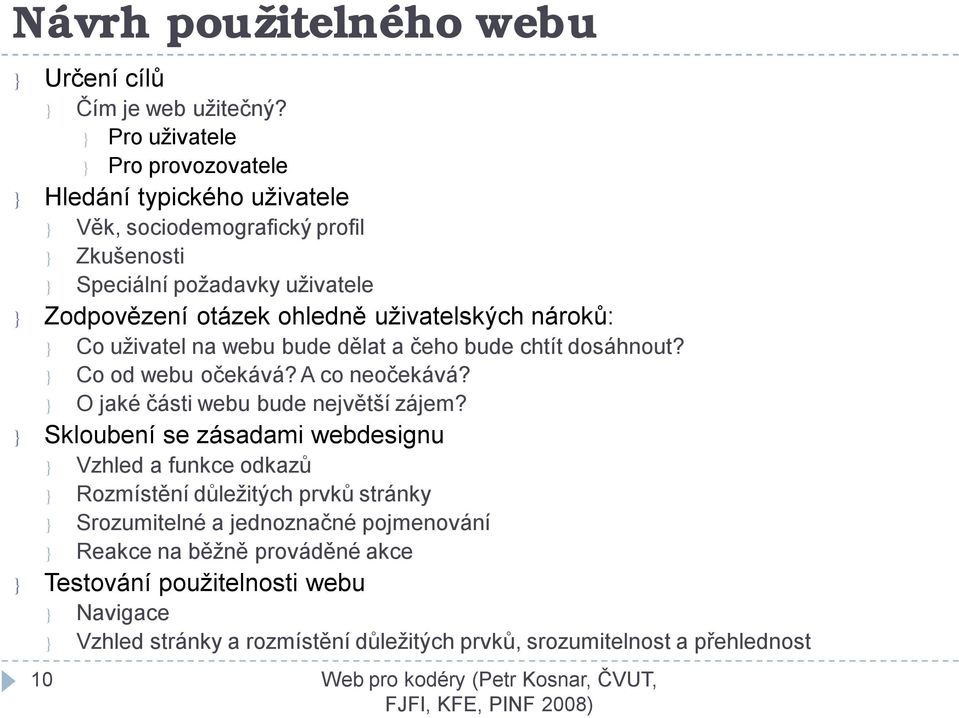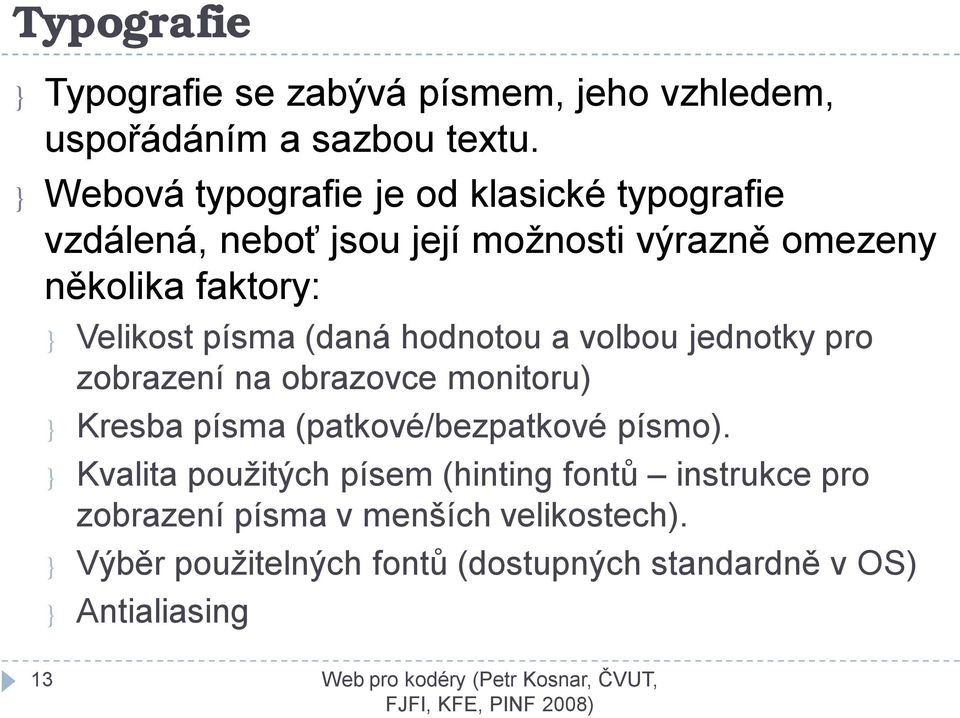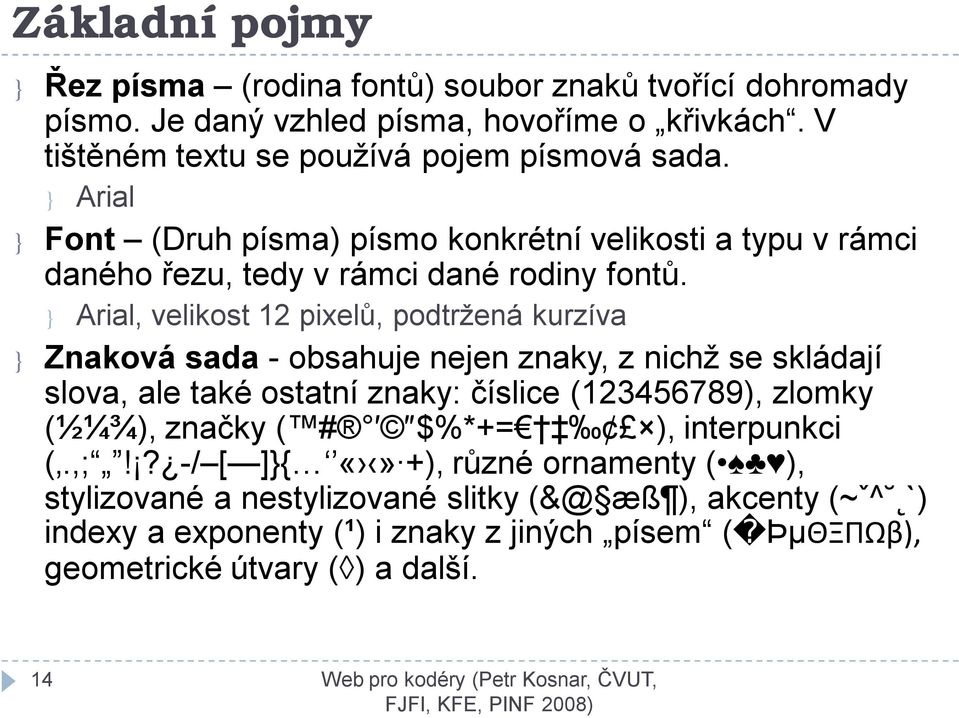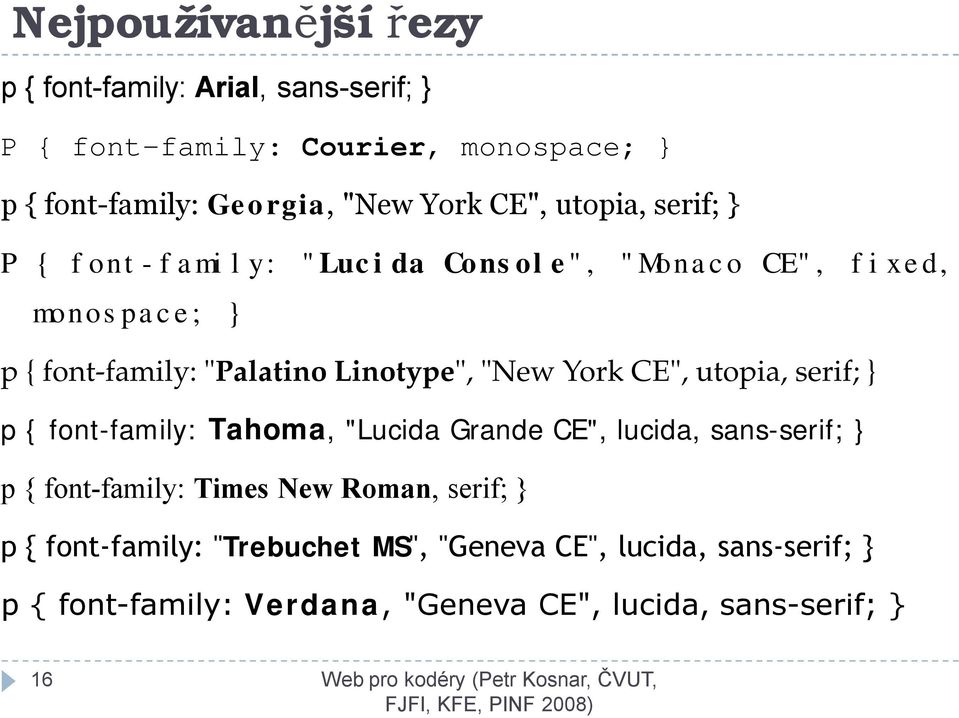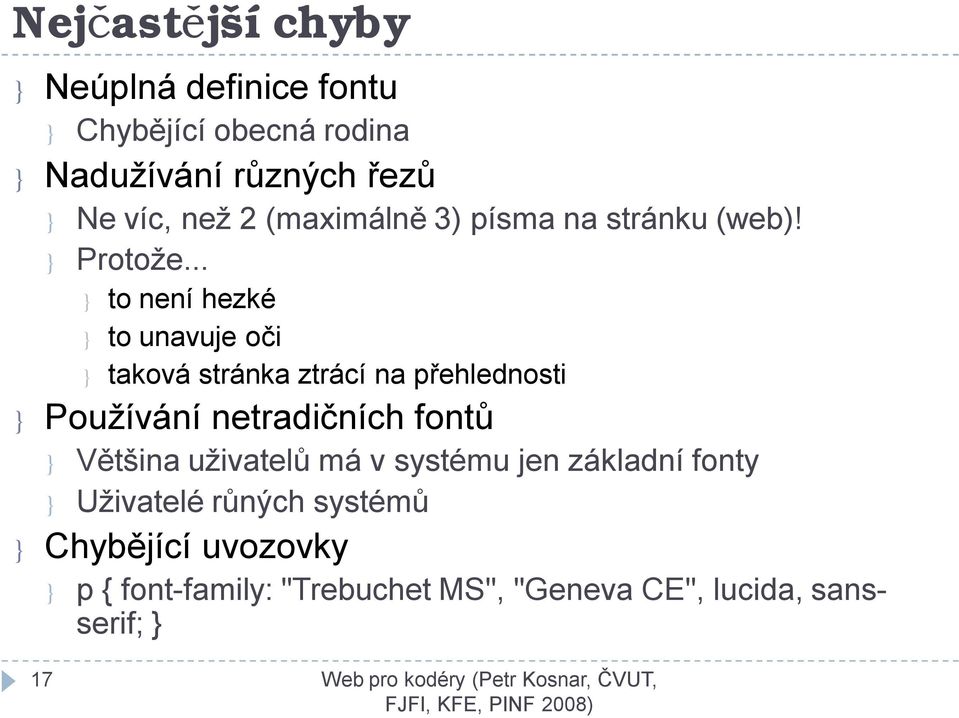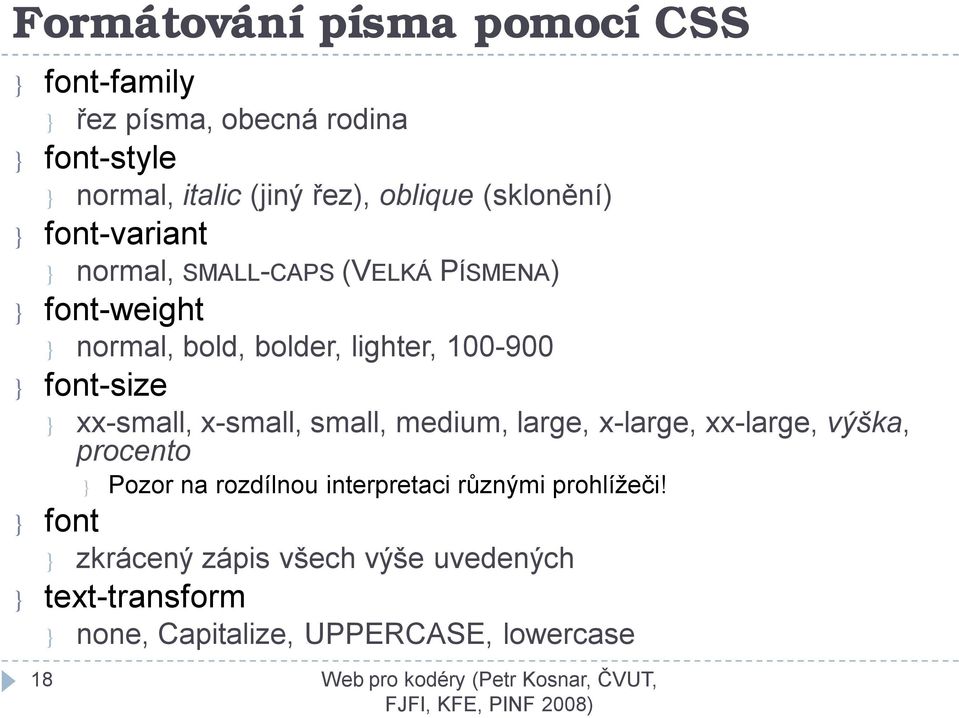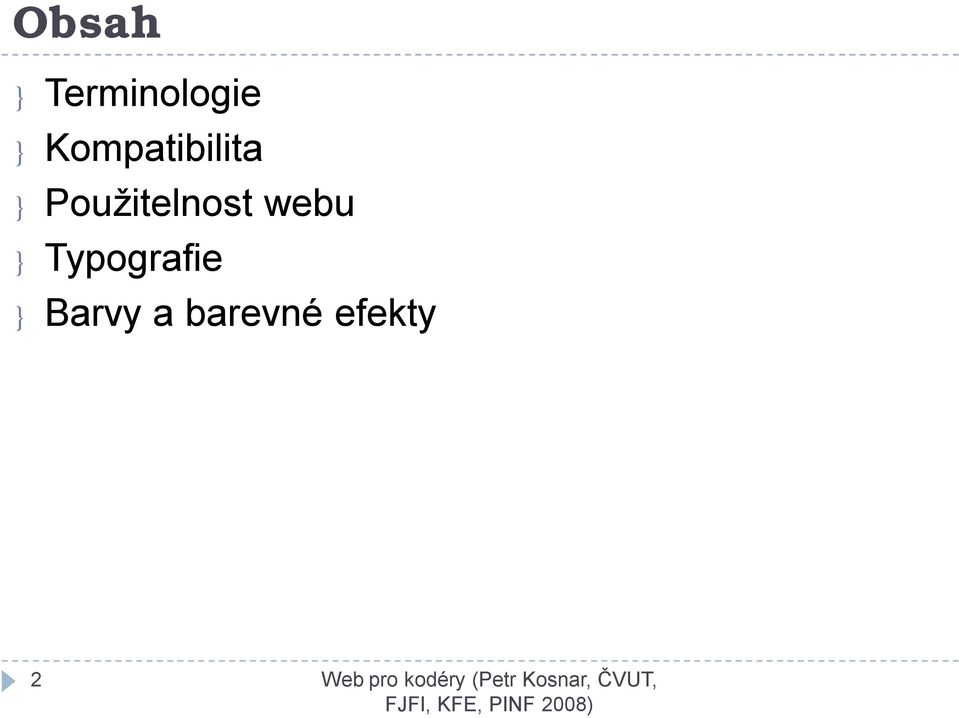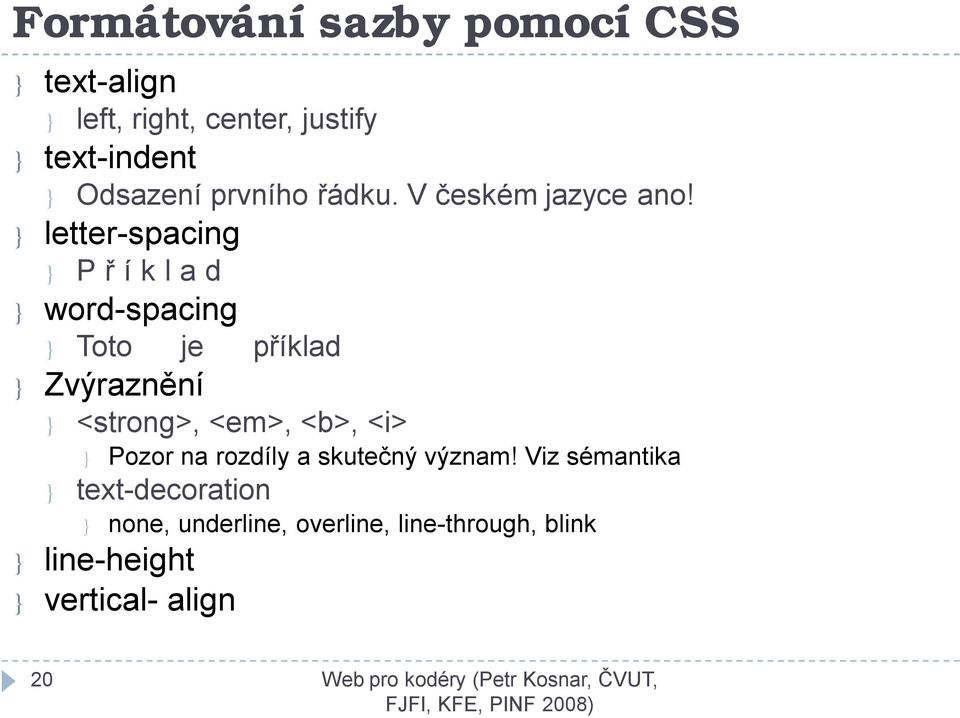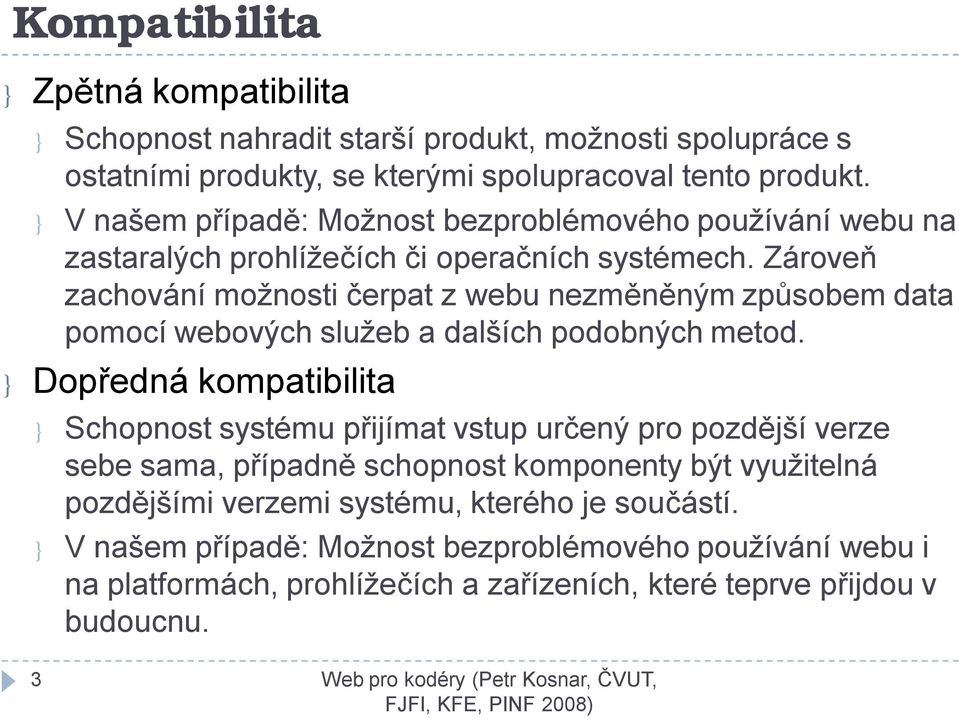
3. Kompatibilita, použitelnost a základy typografie. Web pro kodéry (Petr Kosnar, ČVUT, FJFI, KFE, PINF 2008)
1 3. Kompatibilita, použitelnost a základy typografie Web pro kodéry (Petr Kosnar, ČVUT,
2 Obsah } Terminologie } Kompatibilita } Použitelnost webu } Typografie } Barvy a barevné efekty 2
3 Kompatibilita } Zpětná kompatibilita } Schopnost nahradit starší produkt, možnosti spolupráce s ostatními produkty, se kterými spolupracoval tento produkt. } V našem případě: Možnost bezproblémového používání webu na zastaralých prohlížečích či operačních systémech. Zároveň zachování možnosti čerpat z webu nezměněným způsobem data pomocí webových služeb a dalších podobných metod. } Dopředná kompatibilita } Schopnost systému přijímat vstup určený pro pozdější verze sebe sama, případně schopnost komponenty být využitelná pozdějšími verzemi systému, kterého je součástí. } V našem případě: Možnost bezproblémového používání webu i na platformách, prohlížečích a zařízeních, které teprve přijdou v budoucnu. 3
4 Zpětná kompatibilita } Neexistuje stoprocentní zpětná kompatibilita } Přesněji: lze jí dosáhnout pouze vynaložením neúměrného úsilí a konečný výsledek je celkově vzato špatný. Navíc s minimální užitnou hodnotou. } Příklad: Netscape 1.0 nepodporuje ani HTML tabulky. Nemluvě o CSS, DOM a dalších vymoženostech posledních let. } Je potřeba si určit hranici zpětné kompatibility, kterou svým stránkám poskytneme (nejstarší podporovaný prohlížeč) } hlubší zpětná kompatibilita s sebou přináší rozšiřování kódu o nestandardní kusy kódu určené pro specifické zastaralé prohlížeče. Zároveň je potřeba nějaký obslužný mechanismus, který předloží zastaralým prohlížečům tu verzi stránek, která je jim určena. 4
5 Dopředná kompatibilita } Principielně obtížné, není znám budoucí vývoj. } Spoléhá se tedy na zpětně kompatibilní budoucí browsery } Dodržování standardů nejnovějších verzí XHTML přináší možnost větší interoperability a vysokou pravděpodobnost podpory do budoucna. } Nebude potřeba vytvářet vícero verzí stránky pro různé nové prohlížeče } Minimum problémů s dostupností díky všeobecné podpoře, oblíbenosti a rozvoji XML } Strukturální kód pro pozdější zpracovávání jako jakékoliv jiné XML 5
6 Platformy, prohlížeče, média } Počítejme s tím, že náš web by měl být přizpůsobený pro: } Operační systémy: } Windows, GNU/Linux, MacOS, PalmOS, Windows Mobile, Symbian } Prohlížeče: } Internet Explorer, Opera, Firefox, Safari, Opera mini } Zařízení: } PC, PDA, Smartphone, hlasová čtečka, projektor, tiskárna 6
7 Přirozená kompatibilita XHTML } XHTML jako člen rodiny XML je přirozeně kompatibilní s ostatními XML formáty a aplikacemi. } XHML zobrazují i zastaralé prohlížeče z dob, kdy specifikace XHTML neexistovala nebo byla v plenkách. } Jedna verze kódu pro všechny možnosit použití pro zobrazení na různých zařízeních, v různých prostředích a prohlížečích... } XHTML 1.0 existuje ve třech verzích: } Strict, Transitional a Frameset } Nejnovější verze: XHTML 1.1 } XHTML 2.0 ve stádiu Working Draft } XHTML má samozřejmě i své odpůrce 7
8 Použitelnost } Jak snadno uživatel najde na webu to, co hledá? } Jak snadno se uživatel naučí web ovládat? } Bude se muset na každé stránce se systémem znovu učit zacházet? } Když už se uživatel naučí web ovládat, jak efektivně s ním pracuje? } Jak dobře si zapamatuje styl ovládání webu? Přijde mu tento styl přirozený a nenásilný? } Kolik udělá uživatel při používání webu chyb? Dokáže nakonec splnit svůj cíl? Najde to, co hledal? } Je pro uživatele používání webu příjemné? Vrátí se? } Jsou informace, které uživatel našel platné a aktuální? 8
9 Myšlenka... Televizní stanice neříkají divákům, jak ovládat dálkový ovládač. Novináři neinstruují čtenáře, jak vyndat noviny ze schránky. Je čas, aby webové stránky přestaly říkat návštěvníkům, jak ovládat odkazy. Jason Roberts 9
10 Návrh použitelného webu } Určení cílů } Čím je web užitečný? } Pro uživatele } Pro provozovatele } Hledání typického uživatele } Věk, sociodemografický profil } Zkušenosti } Speciální požadavky uživatele } Zodpovězení otázek ohledně uživatelských nároků: } Co uživatel na webu bude dělat a čeho bude chtít dosáhnout? } Co od webu očekává? A co neočekává? } O jaké části webu bude největší zájem? } Skloubení se zásadami webdesignu } Vzhled a funkce odkazů } Rozmístění důležitých prvků stránky } Srozumitelné a jednoznačné pojmenování } Reakce na běžně prováděné akce } Testování použitelnosti webu } Navigace } Vzhled stránky a rozmístění důležitých prvků, srozumitelnost a přehlednost 10
11 Nezapomeňte... } Přehledná a intuitivní navigace, odkazy naznačují co se pod nimi skrývá } Navigační menu, nadpis webu, případně logo umístit na všech stránkách na stejném místě } Na každé stránce by mělo být uživateli zřejmé, kde se v rámci webu nachází a jaký je účel této stránky } Z každé stránky by měl vést odkaz na úvodní stránku a na hlavní stránku sekce, ve které se nachází } Pořadí, velikost a výraznost prvků odpovídají jejich významu a důležitosti } Není na stránce něco zbytečně, nějaký rušivý element? 11
12 12
13 Typografie } Typografie se zabývá písmem, jeho vzhledem, uspořádáním a sazbou textu. } Webová typografie je od klasické typografie vzdálená, neboť jsou její možnosti výrazně omezeny několika faktory: } Velikost písma (daná hodnotou a volbou jednotky pro zobrazení na obrazovce monitoru) } Kresba písma (patkové/bezpatkové písmo). } Kvalita použitých písem (hinting fontů instrukce pro zobrazení písma v menších velikostech). } Výběr použitelných fontů (dostupných standardně v OS) } Antialiasing 13
14 Základní pojmy } Řez písma (rodina fontů) soubor znaků tvořící dohromady písmo. Je daný vzhled písma, hovoříme o křivkách. V tištěném textu se používá pojem písmová sada. } Arial } Font (Druh písma) písmo konkrétní velikosti a typu v rámci daného řezu, tedy v rámci dané rodiny fontů. } Arial, velikost 12 pixelů, podtržená kurzíva } Znaková sada - obsahuje nejen znaky, z nichž se skládají slova, ale také ostatní znaky: číslice ( ), zlomky (½¼¾), značky ( # $%*+= ), interpunkci (.,;!? -/ [ ]}{ +), různé ornamenty ( ), stylizované a nestylizované slitky (&@ æß ), akcenty (~ˇ^ `) indexy a exponenty (¹) i znaky z jiných písem ( ÞµΘΞΠΩβ), geometrické útvary ( ) a další. 14
15 Obecné rodiny písem Obecná rodina Popis Typická písma Ukázka sans-serif Bezpatkové písmo Arial, Helvetica sans-serif serif monospace Patkové písmo Neproporcionální písmo Times New Roman, Times Courier, Courier New serif monospace fantasy Ozdobné písmo různé FANTASY cursive Ozdobná kursiva různé cursive Patkové a bezpatkové písmo dostalo svůj název podle zobáčků, tedy patek (či jejich absence) na otevřených koncích křivek, které tvoří danou literu. Neproporcionální znamená, že všechny znaky takového řezu mají stejnou horizontální šířku (využívá se k prezentaci zdrojových kódů, atp.) 15
16 Nejpoužívanější řezy p { font-family: Arial, sans-serif; } P { font-family: Courier, monospace; } p { font-family: Georgia, "New York CE", utopia, serif; } P { font-family: "Lucida Console", "Monaco CE", fixed, monospace; } p { font-family: "PalatinoLinotype", "New York CE", utopia, serif; } p { font-family: Tahoma, "Lucida Grande CE", lucida, sans-serif; } p { font-family: Times New Roman, serif; } p { font-family: "Trebuchet MS", "Geneva CE", lucida, sans-serif; } p { font-family: Verdana, "Geneva CE", lucida, sans-serif; } 16
17 Nejčastější chyby } Neúplná definice fontu } Chybějící obecná rodina } Nadužívání různých řezů } Ne víc, než 2 (maximálně 3) písma na stránku (web)! } Protože... } to není hezké } to unavuje oči } taková stránka ztrácí na přehlednosti } Používání netradičních fontů } Většina uživatelů má v systému jen základní fonty } Uživatelé růných systémů } Chybějící uvozovky } p { font-family: "Trebuchet MS", "Geneva CE", lucida, sansserif; } 17
18 Formátování písma pomocí CSS } font-family } řez písma, obecná rodina } font-style } normal, italic (jiný řez), oblique (sklonění) } font-variant } normal, SMALL-CAPS (VELKÁ PÍSMENA) } font-weight } normal, bold, bolder, lighter, } font-size } xx-small, small, medium, large, x-large, xx-large, výška, procento } Pozor na rozdílnou interpretaci různými prohlížeči! } font } zkrácený zápis všech výše uvedených } text-transform } none, Capitalize, UPPERCASE, lowercase 18
19 Sazba textu } Neznámá šířka řádku } -> nelze zabránit vzniku tzv. Řek } Řeky - nepřiměřeně velké mezislovní mezery, které na sebe vhorším případě ještě ve vertikálním směru navazují } Neznámá velikost písma } Uživatelské nastavení v prohlížeči } Šířka řádku nejlépe znaků (včetně mezer) } Nepoužívat sazbu do bloku 19
20 Formátování sazby pomocí CSS } text-align } left, right, center, justify } text-indent } Odsazení prvního řádku. V českém jazyce ano! } letter-spacing } P ř íklad } word-spacing } Toto je příklad } Zvýraznění } <strong>, <em>, <b>, <i> } Pozor na rozdíly a skutečný význam! Viz sémantika } text-decoration } none, underline, overline, line-through, blink } line-height } vertical- align 20
21 Entity } Entity se používají k zapisování nestandardních znaků, pokud nám jejich zapsání neumožňuje použité kódování } Kódování UTF-8 znaky zapisované entitami obsahuje! } Entita se zapisuje ve tvaru &jmeno_entity; 21
22 Mezery } Nedělitelná (zúžená mezera se nepoužívá kvůli slabé podpoře prohlížečů) } Mezi iniciálou a příjmením (P. Kosnar) } Mezi titulem a příjmením (Ing. Novák) } Ve víceslovném názvu (Windows XP) } Mezi hodnotou a jednotkou (10 cm) } Jako oddělovač řádů ( ) } Mezi hodnotou a znakem procenta (účinnost je asi 23 %) } Datumy ( ) } Mezi paragraf a jeho číslo ( 111) } Okolo symbolu & (Plug & Play) } U poměrů (1 : 10) } V matematických vzorcích ( = 30) } Zajišťuje, že se jednopísmenná předložka, spojka či libovolný jeden znak nikdy neobjeví na konci řádku. } Výjimka -spojky a a i vsouřadném poměru, nikoliv však na začátku věty. 22
23 Mezeru nepíšeme } u sportovních výsledků: } Sparta-Slavia: 0:0 } je-li jednotka ve funkci přídavného jména: } 60W žárovka, 10 pivo } před symbol procenta ve smyslu přídavného jména: } 3% úrok (tříprocentní úrok) } při uvádění velikosti úhlu nebo obsahu alkoholu (přestože se jedná o jednotky): } 360, 10 } okolo lomítek: } km/h } za desetinnou čárkou: } 23,4 } u násobků: } 10krát, 10násobně, 10 (10 ) } u časů ve sportovních výsledcích: } viz později Pozor, změna možná významu! zápis x=1-3 můžeme reprodukovat jako: rozsah proměnné x = 1 3 rovnici x =
24 Pomlčka -+ } Spojovník } Spojování slov, } Praha2-Vinohrady, Frýdek-Místek, literárně-hudební soubor, česko-německý slovník } k připojení zvratné částice "li } bude-li, chcete-li } Mínus } Operační symbol s mezerami } 10 3 = 7 } Záporná čísla bez mezer } Teplota dosáhla 18,5 C. } En-pomlčka } ve funkci spojky či předložky (bez mezer) } utkání Sparta Slavia(ve významu proti), } dvojice Voskovec Werich (a), } linka Praha Brno (z-do), } vláda KSČ v letech (od-do). } přestávka v řeči nebo vypuštěného slova (s mezerou) } Můj dům můj hrad. } Volnost rovnost bratrství. } označení celých peněžních částek } Časopis je za Kč 69, 24
25 Způsoby psaní speciálních údajů } Telefonní (faxová) čísla } Mezinárodní formát nnn nnn nnn } } Poštovní směrovací čísla } nnn nn } } Kalendářní data } Den, měsíc a rok oddělujeme pomocí } 24. ledna 2010, } Hodiny a minuty oddělujeme tečkou, minuty a sekundy dvojtečkou, sekundy a setiny sekund desetinnou čárkou, (mezery se nepíšou). } hod, 2 h 30 min, 3:15,23 min. } J. N. uběhl trať v čase 5:32:15,25 (tzn. 5 hodin, 32 minut, 15 sekund a 25 setin sekundy). } Rok můžeme zkrátit na dvě číslice v případě spojení dvou letopočtů spojovníkem či lomítkem ( , 1994/95) nebo ve zvláštních spojeních (INVEX 99, INVEX 99). Nebo v případě výtvarného zájmu. 25
26 Další často používané entity } Matematické znaky. } ± ± } } } } } } ¼ ¼ } ½ ½ } ¾ ¾ } Uvozovky } Horní } dolní } Další... } } } } } 26
27 Interpunkce } Mezera } za interpunkčním znaménkem, nikoliv před. } Říkal, že firma ABC, s. r. o., která zde sídlila, je zrušená. } Výpustka (trojtečka) } tam, kde je vypuštěná či nedopovězená část věty } Ještě jednou mi zasedneš místo a } Pomlčka ani spojovník nesmí stát na začátku řádku } Mladí ležáci staří žebráci. } Apostrof nahrazuje vynechané písmeno. ' } Na požádání si stáh' i kalhoty. 27
28 Skladba stránky } Úvodní odstavec krátký (11 slov) } Titulek, podtitulek, perex, mezititulky } Číslované výčty místo nečíslovaných (odrážkových) } volný řádek mezi odstavci (vertikální odsazení) } Čím méně zvýraznění, tím čitelnější text } Má-li být text zviditelněn, dejme mu víc volného prostoru } Dlouhé řádky se obtížně čtou } Rozdělení: Záhlaví, hlavní obsah, pata 28
29 Barvy a grafické efekty } Musí být zajištěn dostatečný kontrast } Aby byla stránka čitelná i na nekvalitním nebo poškozeném monitoru, displeji osvětleném sluncem... } Minimum rušivých grafických efektů } Blikání, výrazné barevné kombinace, mnoho barev pohromadě 29
30 Kontrast Je nutný dostatečný rozdíl v odstínu, nasycení a světlosti 30
31 Další informace } } } } Steve Krug: Don t Make Me Think } Jakob Nielsen: Usability Engineering } Jesse J. Garrett: The Elements of User Experience } Pavel Kočička, Filip Blažek: Praktická typografie, Computer Press, Brno, 2004, ISBN } } } } } } } } } 31
32 Kontrolní úkol } Vytvořte stránku s nějakým odborným obsahem, kde jsou smysluplně využité alespoň 4 různé XHTML entity. } Stránku graficky zpracujte, aby působila jednoduše, přehledně a její obsah byl čitelný. } Ocením originální estetické zpracování } Avšak pozor na respektování pravidel z této přednášky! } Požadavky: } Validní a sémanticky správný XHTML a CSS } Oddělení obsahu od prezentace } Dodržení zásad kompatibility a snadné použitelnosti } Dodržení typografických pravidel } Odpovídající barevné zpracování 32
Základní typografická pravidla
Základní typografická pravidla 1. část materiál pro 12IPG J. Blažej, 2012 Úvod Typografie se zabývá písmem, jeho vzhledem, uspořádáním a sazbou textu. umělecko-technický obor ne vždy jasná pravidla legislativa
KASKÁDOVÉ STYLY - PÍSMO
KASKÁDOVÉ STYLY - PÍSMO Název školy Obchodní akademie, Vyšší odborná škola a Jazyková škola s právem státní jazykové zkoušky Uherské Hradiště Název DUMu Kaskádové styly písmo Autor Zdeněk Hrdina Datum
Maturitní otázka číslo 23 strana 1 z 5. Typografie
Maturitní otázka číslo 23 strana 1 z 5 Typografie je vědní obor zabývající se sázením textu, hlavně jeho grafickou stránkou. S příchodem počítačů máme k dispozici různé DTP programy (DeskTop
Střední průmyslová škola a Vyšší odborná škola technická Brno, Sokolská 1
Střední průmyslová škola a Vyšší odborná škola technická Brno, Sokolská 1 Šablona: Název: Téma: Autor: Inovace a zkvalitnění výuky prostřednictvím ICT Design a vzhledové vlastnosti webových stránek Vlastnosti
Počítačová typografie
Počítačová typografie Typografie je nauka o tom, jak má tiskovina vypadat. Proč se o typografii učíme? Každý z nás běžně připravuje nějakou tiskovinu a požadavky na její kvalitu a zpracování jsou všude
Předmět: Typografie na webu
Registrační číslo projektu: CZ.1.07/1.4.00/21.3712 Škola adresa: Základní škola T. G. Masaryka Ivančice, Na Brněnce 1, okres Brno-venkov, příspěvková organizace Na Brněnce 1, Ivančice, okres Brno-venkov
Návrh stránek 4IZ228 tvorba webových stránek a aplikací
4IZ228 tvorba webových stránek a aplikací Jirka Kosek Poslední modifikace: $Date: 2013/12/12 20:40:58 $ Obsah Úvod... 3 Recept na dobré webové stránky... 4 Použitelnost... 5 Jak se pozná použitelný web...
Blokový model v CSS:
Blokový model v CSS: Vlastnosti textu Vlastnost Hodnoty Standardní hodnota Aplikuje se na Dědí se Popis word-spacing normal, délka normal o kolik se zvětší mezera mezi slovy letter-spacing
Webová grafika, struktura webu a navigace, použitelnost a přístupnost
Webová grafika, struktura webu a navigace, použitelnost a přístupnost Martin Kuna martin.kuna@seznam.cz Obsah Webová grafika Rozvržení stránky Typografické zásady Nejčastější chyby Struktura webu a navigace
T Y P O G R A F I E. Tvorba textových dokumentů
T Y P O G R A F I E Tvorba textových dokumentů Počítačová typografie nauka o tom, jak má tiskovina vypadat typus = znak, grafó = píši současné programové vybavení a možnost kvalitního tisku každý může
Word textový editor. Tlačítko Office základní příkazy pro práci se souborem. Karta Domů schránka. písmo. vyjmout. vložit kopírovat.
Word textový editor Tlačítko Office základní příkazy pro práci se souborem Karta Domů schránka vyjmout vložit kopírovat formát písmo velikost písma volba písma barva písma tučné podtržené zvýraznění
pravidla pro grafickou úpravu textů při práci s textovými editory:
Zásady pro vypracování seminární a maturitní práce Úprava písemností zpracovaných textovými editory norma ČSN 01 6910 pravidla pro grafickou úpravu textů při práci s textovými editory: určuje způsob psaní
Přehled základních html tagů
Přehled základních html tagů h1... hlavní nadpis h2... podnadpisy h3... podnadpisy další úrovně p... odstavec strong... tučné písmo b... tučné písmo em... kurzíva i... kurzíva br... zalomení řádku ol...
TVORBA WEBOVÝCH STRÁNEK
TVORBA WEBOVÝCH STRÁNEK Výukový modul TWS_03b Ing. Pavel Chmiel, Ph.D. UNIV 2 - KRAJE Osnova výukového modulu TWS_03b 1. Kaskádové styly (CSS) 2. Vazba CSS na (X)HTML dokument 3. Syntaxe CSS 4. Barva a
Letem ke klíčovým kompetencím aneb Pohádkou o Raškovi to nekončí Metodický materiál ZŠ a MŠ Frenštát pod Radhoštěm, Tyršova 913 2009 2011
Letem ke klíčovým kompetencím aneb Pohádkou o Raškovi to nekončí Metodický materiál ZŠ a MŠ Frenštát pod Radhoštěm, Tyršova 913 2009 2011 Zpracování: Mgr. Marek Křištof ZŠ a MŠ Frenštát pod Radhoštěm,
Fonty - praxe, obecné rodiny
Fonty - praxe, obecné rodiny Windows, fonty, internet? Většina profesionálních webových tvůrců operuje nejvýše s těmito základními řezy: Arial, Courier New, Georgia, Lucida Console, Palatino Linotype,
ZÁKLADY PRÁCE S PC MS Word. Mgr. Petr Jakubec
ZÁKLADY PRÁCE S PC MS Word Mgr. Petr Jakubec 1 Nejdůležitější panely: Vložit Konce stránek, Konce oddílů, Čísla stránek, Symboly, Odkazy (Poznámka pod čarou, Titulek,...) Formát Písmo, Odstavce, Odrážky
Základní typografická pravidla
Základní typografická pravidla materiál pro 12IPG J. Blažej, 2017 Úvod Typografie se zabývá písmem, jeho vzhledem, uspořádáním a sazbou textu. umělecko-technický obor ne vždy jasná jednoznačná pravidla
Referenční přehled vlastností CSS1 (Cascading Style Sheets, level 1)
Stránka č. 1 z 9 Referenční přehled CSS1 (Cascading Style Sheets, level 1) Tento dokument shrnuje jdůležitější informace o káskadových stylech dokumentů. Informace vycházejí z oficialního doporučení konsorcia
FORMÁLNÍ NÁLEŽITOSTI PRÁCE TOMÁŠ LÁZNA ZÁŘÍ 2015 T.LAZNA@GMAIL.COM
FORMÁLNÍ NÁLEŽITOSTI PRÁCE TOMÁŠ LÁZNA ZÁŘÍ 2015 T.LAZNA@GMAIL.COM PRÁCE SOČ 20 30 stran + přílohy Obvyklá struktura Pravopis Grafická úprava, typografie Vazba typicky kroužková nebo hřbet STRUKTURA ODBORNÉ
! Nauka o tom, jak má tiskovina vypadat. ! dobře čitelná. ! snadná orientace v textu. ! estetické působení. ! Klasické umělecké řemeslo
Počítačová typografie úvod Aplikační software na PC Počítačová typografie původní verze Mgr. Lucie Pelikánová úpravy a rozšíření RNDr. Jan Preclík! Nauka o tom, jak má tiskovina vypadat! dobře čitelná!
Typografická a estetická pravidla. Daniela Špačková
Typografická a estetická pravidla Daniela Špačková Používání a kombinování písem Pro tištěné texty: písmo patkové, např. Times New Roman Pro prezentace: písmo bezpatkové, např. Arial Nadpisy mohou být
Textové editory. Ing. Luděk Richter
Textové editory Ing. Luděk Richter Střední škola, Havířov-Šumbark, Sýkorova 1/613, příspěvková organizace Tento výukový materiál byl zpracován v rámci akce EU peníze středním školám - OP VK 1.5. Výuková
Kaskádové styly (CSS) Cascading Style Sheets
CSS verze 22.11. 2007 1 Kaskádové styly (CSS) Cascading Style Sheets Existují 3 druhy zápisu CSS do webové stránky a) Vložením tagu STYLE do hlavičky dokumentu ...definice stylu atributy: type...
STANDARDNÍ APLIKAČNÍ VYBAVENÍ
Projekt Pospolu Práce s textovým procesorem STANDARDNÍ APLIKAČNÍ VYBAVENÍ Autorem materiálu a všech jeho částí, není-li uvedeno jinak, je Bohuslava Čežíková. Struktura prezentace textový dokument písmo
Referenční přehled vlastností CSS1 (Cascading Style Sheets, level 1)
Referenční přehled CSS1 (Cascading Style Sheets, level 1) Tento dokument shrnuje jdůležitější informace o káskadových stylech dokumentů. Informace vycházejí z oficialního doporučení konsorcia W3C Cascading
Střední škola průmyslová a umělecká, Opava, příspěvková organizace, Praskova 399/8, Opava, 746 01 IČO: 47813121 Projekt: OP VK 1.5
Název a adresa školy: Střední škola průmyslová a umělecká, Opava, příspěvková organizace, Praskova 399/8, Opava, 746 01 IČO: 47813121 Projekt: OP VK 1.5 Název operačního programu: OP Vzdělávání pro konkurenceschopnost
Pomocník aneb Když hlava nepostačí
Pomocník aneb Když hlava nepostačí Obsah I. Interpunkční znaménka... 2 Tečka... 2 Čárka... 2 Dvojtečka... 3 Středník... 3 Uvozovky... 3 Apostrof... 3 Spojovník/pomlčka/dlouhá pomlčka... 3 Tři tečky...
Typografická pravidla
VY_32_INOVACE_In 6.,7.05 Typografická pravidla Anotace: Žák se seznámí s typografickými pravidly. Procvičí využití typografických pravidel v praxi. Pracuje na svém žákovském počítači. Vzdělávací oblast:
Typografické míry. Měrné systémy: 1. evropský, tzv. Didôtův. 2. anglosaský. Základní jednotka je typografický bod.
Typografické míry Měrné systémy: 1. evropský, tzv. Didôtův 2. anglosaský Základní jednotka je typografický bod. E 1 b = 0.3759 mm cicero 12 b A 1 pt= 0.351 mm pica 12 pt 02 1 Měrné jednotky TEXu: pt pc
KAPITOLA 3 - ZPRACOVÁNÍ TEXTU
KAPITOLA 3 - ZPRACOVÁNÍ TEXTU KLÍČOVÉ POJMY textové editory formát textu tabulka grafické objekty odrážky a číslování odstavec CÍLE KAPITOLY Pracovat s textovými dokumenty a ukládat je v souborech různého
Typografická pravidla - úvod
Typografická pravidla - úvod Základní doporučení: Nejdříve napište celý dokument základním písmem, potom teprve formátujte (písmo, odstavec, stránku). Klávesa ENTER se používá POUZE NA KONCI ODSTAVCE,
Publikační manuál GJO Litovel
Publikační manuál GJO Litovel Jak by měly naše dokumenty vypadat? Nastavení stránky Okraje z každé strany 2,5 cm U vícestránkových dokumentů číslovat strany. Formát číslování 1, zarovnat na střed zápatí.
Normalizovaná úprava písemností ČSN
Normalizovaná úprava písemností ČSN 01 6910 www.zlinskedumy.cz 3. Textový sloupec Zahrnuje: Papíry a formáty papíru Druhy a velikost písma Mezery - probrané v samostatné kapitole spolu s pevnými spojeními
CSS (Cascading Style Sheets) Jak se zapisují? externí soubory s koncovkou.css. přímo do www stránky
CSS (Cascading Style Sheets) Jak se zapisují? externí soubory s koncovkou.css přímo do www stránky Externí soubory: stránka se styly
Gymnázium a Střední odborná škola, Rokycany, Mládežníků 1115
Číslo projektu: Gymnázium a Střední odborná škola, Rokycany, Mládežníků 1115 Číslo šablony: 5 Název materiálu: Ročník: Identifikace materiálu: Jméno autora: Předmět: Tématický celek: Anotace: CZ.1.07/1.5.00/34.0410
- Byl změněn způsob psaní dat a časových údajů (podle ČSN EN 28601);
ČESKÁ NORMA ICS 01.140.30 1997 Úprava písemností psaných strojem nebo zpracovaných textovými editory ČSN 01 6910 Srpen Guidelines for Typewriting and Text Presentation Règles pour la dactylographie et
Řekl: V létě 89 zemřela. d Artagnan
x Apostrof odsuvník neplést s jednoduchou uvozovkou Používá se pro vynechání části letopočtu: jaro 98. V cizích jazycích: d Artagnan. porovnejte tvar Řekl: V létě 89 zemřela. d Artagnan x Uvozovky Přisazují
Odkazy se v normálním případě podtrhávají samy, není nutno to nastavovat.
Úprava textu Všechny tagy na formátování textu jsou in-line tagy, to znamená řádkové. Nezalamují za sebou řádek (narozdíl od blokových tagů). Fyzické formátování říká, jak má který
Pravidla pro estetickou úpravu textu
Pravidla pro estetickou úpravu textu Pro vytváření dobře vypadajících dokumentů existují osvědčené zásady a pravidla pro to, aby naše dokumenty byly nejen technicky, ale i esteticky na výši. Používání
Typografie. pro každý den
Typografie pro každý den Okouzlete zákazníka svým designem! Typografie pro každý den! Leták? To zvládnu sám! Znáte to? Asi ano. Každý z nás už musel něco vytvořit. Ať to byl úřední dopis, leták nebo třeba
CSS - stručná reference kaskádových stylů
1. font a parametry písma font, font-family, font-size, font-style, font-variant, font-weight 1.1 font Nastavuje většinu parametrů textu najednou. Jednotlivé atributy naleznete v kapitolách 1.2-1.6 a line-height
PSANÍ ODBORNÉHO TEXTU (např. SOČ, seminární práce)
PSANÍ ODBORNÉHO TEXTU (např. SOČ, seminární práce) Každý text nás reprezentuje, u odborných textů to platí obzvlášť Vše je posuzováno ze tří hledisek (nic z toho se nesmí zanedbat): obsah podloženost tvrzení,
Pokyny k vypracování absolventské práce
Základní škola a Mateřská škola Bělá pod Pradědem, příspěvková organizace tel.: 584 412 084 e-mail: zsadolfovice@jen.cz Adolfovice 170 web: http://zsadolfovice.cz IČO: 75029456 790 01 Jeseník Pokyny k
Reprodukce textových předloh
fialar@kma.zcu.cz Podpořeno z projektu FRVŠ 584/2011 Druhy sazby Podle technologie typografická sazba fotosazba počítačová sazba (DTP, DeskTop Publishing) Podle obsahu a účelu hladká (sazba převážně jedním
Publikační manuál GJO Litovel
Publikační manuál GJO Litovel Jak by měly naše dokumenty vypadat? Nastavení stránky Okraje z každé strany 2,5 cm. (Menu Soubor/Vzhled stránky) U vícestránkových dokumentů číslovat strany. Formát číslování
Základní typografická pravidla
Variace 1 Základní typografická pravidla Autor: Mgr. Jaromír JUŘEK Kopírování a jakékoliv další využití výukového materiálu je povoleno pouze s uvedením odkazu na www.jarjurek.cz. 1. Základní typografická
Střední průmyslová škola strojnická Vsetín. Předmět Druh učebního materiálu Typografická pravidla pro psaní dokumentů
Název školy Číslo projektu Autor Střední průmyslová škola strojnická Vsetín CZ.1.07/1.5.00/34.0483 Ing. Martin Baričák Název šablony III/2 Název DUMu 1.2 Základní typografická pravidla I. Tematická oblast
Mimochodem, co je CSS? Formátování HTML. Drobný problém. Základy práce se styly. Trojí použití CSS. Přímo (in-line)
Mimochodem, co je CSS? CSS vzniklo někdy kolem roku 1997. Je to kolekce metod pro grafickou úpravu webových stránek. Ta zkratka znamená Cascading Style Sheets, česky "kaskádové styly". Kaskádové, protože
PODPORA ELEKTRONICKÝCH FOREM VÝUKY
I N V E S T I C E D O R O Z V O J E V Z D Ě L Á V Á N Í PODPORA ELEKTRONICKÝCH FOREM VÝUKY CZ.1.07/1.1.06/01.0043 Tento projekt je financován z prostředků ESF a státního rozpočtu ČR. SOŠ informatiky a
Zpracování textů na počítači
Gymnázium, Obchodní akademie a Jazyková škola s právem státní jazykové zkoušky Hodonín Zpracování textů na počítači Jedna z nejrozšířenějších aplikací Dříve výhradně práce vyškolených typografů MS Word
Informační zdroje. Pravidla českého pravopisu Česká norma ČSN 01 6910 Úprava písemností psaných strojem nebo zpracovaných textovými editory
Informační zdroje Pravidla českého pravopisu Česká norma ČSN 01 6910 Úprava písemností psaných strojem nebo zpracovaných textovými editory http://wes.wyda.cz/pocitace/texty/uprava/obsah.htm http://home.pf.jcu.cz/~edpo/pravidla/obsah.html
TNPW1 Cvičení
13.10.2015 aneta.bartuskova@uhk.cz Úvod do CSS 13.10.2015 aneta.bartuskova@uhk.cz Výchozí styly prohlížeče Pokud nepřiřadíme elementům žádný styl v CSS, formátují se výchozími hodnotami prohlížeče (v CSS
Základní pravidla typografie
Základní pravidla typografie Jak zformátovat text na počítači Dostupné z Metodického portálu www.rvp.cz, ISSN: 1802-4785, financovaného z ESF a státního rozpočtu ČR. Provozováno Výzkumným ústavem pedagogickým
HTML - Úvod. Zpracoval: Petr Lasák
HTML - Úvod Zpracoval: Petr Lasák Je značkovací jazyk, popisující obsah HTML stránek Je z rodiny SGML jazyků, jako např. XML, DOCX, XLSX Nejedná se o programovací ale značkovací jazyk Dynamičnost dodávají
Typogr afie a úprava textů. Martin Raus
Typogr afie a úprava textů Martin Raus Obsah Psaní mezer...3 Nedělitené mezery a jednopísmenné předložky...3 Úzké mezery...3 Pomlčky...3 Uvozovky...4 Trojtečka...4 Sazba na praporek, na střed a do bloku...4
Obsah. Úvod... 9. Barevná kompozice... 16 Světlo... 18 Chromatická teplota světla... 19 Vyvážení bílé barvy... 20
Obsah Úvod.............................................................................................. 9 Historie grafického designu a tisku..................................... 10 Od zadání k návrhu..............................................................
22. Tvorba webových stránek
22. Tvorba webových stránek Webové stránky jsou spolu s elektronickou poštou nejpoužívanější prostředky internetu. Brouzdáme li internetem používáme nějaký prohlížeč. To, co vidíme na obrazovce v prohlížeči
Název: Design webu Anotace:
Registrační číslo projektu: CZ.1.07/1.4.00/21.3712 Škola adresa: Základní škola T. G. Masaryka Ivančice, Na Brněnce 1, okres Brno-venkov, příspěvková organizace Na Brněnce 1, Ivančice, okres Brno-venkov
Tvorba webu. Kaskádové styly (CSS) Martin Urza
Tvorba webu Kaskádové styly (CSS) Martin Urza Motivace Proč používat kaskádové styly k formátování HTML? Dovolují více možností formátování než klasické HTML atributy a stále přibývají další (možnosti).
Zásady a doporučení pro tvorbu prezentací SZŠ A VOŠ MERHAUTOVA 15, BRNO
Zásady a doporučení pro tvorbu prezentací SZŠ A VOŠ MERHAUTOVA 15, BRNO Struktura prezentace Titulní snímek název prezentované práce, jméno autora, jméno vedoucího práce Úvodní snímek zadání projektu,
Základní typografická pravidla
Základní typografická pravidla VY_32_INOVACE_In 6.,7.05 Anotace: V prezentaci si žák upevní základní typografická pravidla. V jejím průběhu si daná pravidla procvičuje na svém žákovském počítači. Vzdělávací
HTML Hypertext Markup Language
HTML Hypertext Markup Language je jazyk určený na publikování a distribuci dokumentů na Webu velmi jednoduchý jazyk používá ho mnoho uživatelů má výkonné prostředky (příkazy) k formátování dokumentů (různé
Základy typografie a zpracování textů na počítači. Helena Novotná Jiří Rybička
Základy typografie a zpracování textů na počítači Helena Novotná Jiří Rybička 2 Proč typografie? motto: Podobně jako je morálně nepřípustné publikovat texty s pravopisnými chybami, je stejně nepřípustné
Výňatek normalizované úpravy písemností ČSN 01 6910
Výňatek normalizované úpravy písemností ČSN 01 6910 I. Členící (interpunkční) znaménka 1. Tečka, čárka, dvojtečka, středník, vykřičník, otazník - Připojují se těsně bez mezery za předcházející slovo, zkratku,
Webové stránky. 5. Kaskádové styly formátování textu. Datum vytvoření: 3. 10. 2012. str ánk y. Vytvořil: Petr Lerch. www.isspolygr.
Webové stránky 5. Vytvořil: Petr Lerch www.isspolygr.cz Datum vytvoření: 3. 10. 2012 Webové Strana: 1/11 Škola Ročník Název projektu Číslo a název šablony Autor Tématická oblast Název DUM
text, hladká sazba, typografická pravidla
Hladká sazba typografická pravidla Číslo projektu Kódování materiálu Označení materiálu Název školy Autor Anotace CZ.1.07/1.5.00/34.0950 VY_32_INOVACE_inf2_txv04 txv04_typografie.pdf Gymnázium Kladno Mgr.
Základy redakční práce. Eva Juláková Tel:
Základy redakční práce Eva Juláková E-mail: julakova@kav.cas.cz Tel: 607 565 211 ZÁKLADNÍ POPIS KNIHY desky (obálka) přebal záložka (text) předsádka patitul protititul titul anotační stránka první strana
Základní informace o modulu
12 12.1 Výuka modulu Vyučující Jméno Telefon E-mail VEDOUCÍ MODULU Doc. Ing. Jiří Rybička, Dr. 545 13 22 23 rybicka@mendelu.cz Cíl výuky v modulu Získání základního přehledu o principech funkce a možnostech
Inovace výuky prostřednictvím šablon pro SŠ
Název projektu Číslo projektu Název školy Autor Název šablony Název DUMu Stupeň a typ vzdělávání Vzdělávací oblast Vzdělávací obor Tematický okruh Inovace výuky prostřednictvím šablon pro SŠ CZ.1.07/1.5.00/34.0748
Pokyny pro vypracování maturitního projektu
Pokyny pro vypracování maturitního projektu Prostudujte si prosím pečlivě následující pokyny k vypracování maturitního projektu. Maturitní projekt musí obsahovat: 1. Titulní strana (nečísluje se) Obsahuje:
Číslo projektu: CZ.1.07/1.5.00/34.0036 Název projektu: Inovace a individualizace výuky
Číslo projektu: CZ.1.07/1.5.00/34.0036 Název projektu: Inovace a individualizace výuky Autor: Mgr. Jitka MACHÁTOVÁ Název materiálu: Pravidla pro psaní textů Označení materiálu: Datum vytvoření: 10. 10.
Tvorba prezentace. RNDr. Zbyšek Posel, Ph.D. katedra informatiky, PřF Univerzita J. E. Purkyně v Ústí nad Labem. Email: Zbysek.Posel@ujep.
Tvorba prezentace RNDr. Zbyšek Posel, Ph.D. katedra informatiky, PřF Univerzita J. E. Purkyně v Ústí nad Labem Email: Zbysek.Posel@ujep.cz Obsah A. Teoretická část Zásady tvorby prezentace Přednes prezentace
TYPOGRAFIE SKRYTÁ TVÁŘ WEBDESIGNU
TYPOGRAFIE SKRYTÁ TVÁŘ WEBDESIGNU Ing. Tomáš Kostka UNIV 2 KRAJE; TWS_02 Motto: Profesionální dokument (web) musí být správně nejen gramaticky, ale i typograficky. 1 Typografie je umělecko-technický
CSS vlastnosti - stručný prehľad. Vlastnosti písma. Vlastnosti farby a pozadí. font-family. font-style. font-variant. font-weight. font-size.
Page 1 of 6 CSS vlastnosti - stručný prehľad Vlastnosti písma font-family rodina písma font-style styl písma font-variant varianta písma font-weight duktus písma font-size veľkosť písma font písmo
2. Základní pravidla hladké sazby. Typografie
2. Základní pravidla www.isspolygr.cz Vytvořila: Ivana Michálková Vytvořeno dne: 7. 9. 2012 Strana: 1/11 Škola Integrovaná střední škola polygrafi cká, Ročník 1. ročník (SOŠ, SOU) Název projektu Interaktivní
Adobe InDesign. typografické pojmy
Lekce 2 typografické pojmy Typografie = nauka o tom, jak má tiskovina vypadat, aby byla dobře čitelná, snadno se v ní orientovalo a aby působila esteticky. Typografie je také klasické umělecké řemeslo,
K 2 - Základy zpracování textu
Radek Maca Makovského 436 Nové Město na Moravě 592 31 tel. 0776 / 274 152 e-mail: rama@inforama.cz http://www.inforama.cz K 2 - Základy zpracování textu Mgr. Radek Maca Word I 1 slide ZÁKLADNÍ POJMY PRVKY
Tvorba webových stránek
Tvorba webových stránek Kaskádové styly Úprava vzhledu webové stránky pomocí atributů má několik nevýhod a úskalí. Atributy nabízejí málo možností úprav. Obtížně se sjednocují změny na různých částech
Přehled vlastností stylů
Přehled stylů Styly jsou ds jefektivnějším způsobem, jak ovládat grafický vzhled strák. Definují přes padesát, které slouží k vizuálních atributů elementů. V následujících tematicky rozčleněných tabulkách
ŠKODA Portal Platform
ŠKODA Portal Platform Struktura LESS stylů Jan Obrátil Účel dokumentu Účelem tohoto dokumentu je vysvětlit strukturu stylů v Portálové Platformě tak, aby bylo možné je správně použít a rozšířit je pro
CSS Selektory tříd a ID, dědičnost, další vlastnosti. Formátování HTML dokumentu, které je více či méně oddělené od obsahu Způsoby implementace
CSS Selektory tříd a ID, dědičnost, další vlastnosti Internetové publikování 1 Cascading Style Sheets Formátování HTML dokumentu, které je více či méně oddělené od obsahu Způsoby implementace Specifikace
Typografie? Co to vlastně je?
TYPOGRAFIE - ÚVOD Typografie? Co to vlastně je? Typografie je nauka, která se po staletí zabývá úpravou tiskovin. Nejstarší pravidla, jak ladně sestavovat knihy pocházejí z dob Gutenbergových. S příchodem
Vývoj Internetových Aplikací
2 Vývoj Internetových Aplikací HTML a CSS Ing. Michal Radecký, Ph.D. www.cs.vsb.cz/radecky HTML a CSS - Tvorba webových stránek - Struktura - Obsah - Vzhled - Funkcionalita zdroj: http://www.99points.info
Microsoft Office Word 2003
Microsoft Office Word 2003 č. 6 název anotace očekávaný výstup druh učebního materiálu druh interaktivity Microsoft Office Word 2003 - Cesta k základním úpravám Prezentace je zaměřena na úpravy textu v
Programové vybavení. Typografická pravidla I. Mgr. Martin Kolář SOŠ a SOU spojů a informatiky Kolín
Typografická pravidla I 12. 9. 2016 Obsah 1 Typografie Základní informace 2 Základní informace Motto V jednoduchosti je krása! Základní informace Co to je typografie? Typografie je technicko-umělecký směr
Gymnázium Dr. J. Pekaře Mladá Boleslav PRAVIDLA PRO PSANÍ MATURITNÍ PRÁCE
Gymnázium Dr. J. Pekaře Mladá Boleslav Maturitní práce PRAVIDLA PRO PSANÍ MATURITNÍ PRÁCE Předmět: Např. Český jazyk a literatura Datum a rok odevzdání: xx. x. 2016 Jméno a příjmení: Jan NOVÁK Ročník:
CSS Stylování stránek. Zpracoval: Petr Lasák
CSS Stylování stránek Zpracoval: Petr Lasák Cascade Style Sheets Sada stylů každý element má styl svého zobrazení Říká, jak má být element zobrazen, ne co v něm je Do verze HTML 4.0 byl vzhled měněn pouze
[1] Typografie. http://petr.olsak.net/bi-typo.html
[1] Typografie http://petr.olsak.net/bi-typo.html Co je typografie? [2] Forma informací zaznamenaných pomocí písma zejména v případě tisku a při prezentaci na počítačích. Jiné vymezení: Typografie = grafická
FORMÁLNÍ POŽADAVKY NA VYPRACOVÁNÍ SEMINÁRNÍ PRÁCE
FORMÁLNÍ POŽADAVKY NA VYPRACOVÁNÍ SEMINÁRNÍ PRÁCE Vypracováním seminární práce žák prokazuje schopnost sestavit odborný text delšího rozsahu, pracovat s odbornou literaturou i dalšími informačními zdroji
Instrukce pro autory vědeckých spisů
Instrukce pro autory vědeckých spisů Edice PhD Thesis Edice Habilitační a Inaugurační spisy Tisk vědeckých spisů zajišťuje firma NOVPRESS s. r. o. Z organizačních důvodů se prosím pro všechny informace
Základy WWW publikování
Ing. Igor Kopetschke Oddělení aplikované informatiky Ústav nových technologií a aplikované informatiky Fakulta mechatroniky a mezioborových inženýrských studií Technická univerzita v Liberci Email : igor.kopetschke@tul.cz
POKYNY PRO TYPOGRAFICKOU ÚPRAVU TEXTU
POKYNY PRO TYPOGRAICKOU ÚPRAVU TEXTU Většina typografických pravidel vychází z aktuálních pravidel českého pravopisu, která je nutno dodržovat. Uvozovky. V českých textech je třeba sázet české, tzn. typografické
Úvod do počítačové typografie
Úvod do počítačové typografie Písma Vybraná pravidla sazby textu Tento text si klade za cíl seznámit čtenáře alespoň se základními pojmy počítačové typografie. Donedávna před příchodem počítačů do této
OBSAH ÚVOD... ODSTAVEC PÍSMO...
OBSAH ÚVOD... ODSTAVEC... Z arovnání... Počítačové zarovnání... Členení odstavců... Odstavcová zarážka Odstavcové zarážky v programech Bez odstavcové zarážky Předsazený text Grafická zarážka Další úpravy
Microsoft Office. Word typografická a estetická pravidla
Microsoft Office Word typografická a estetická pravidla Karel Dvořák 2011 Typografie je dobrých pět set let rozvíjená nauka o sazbě a úpravě tiskovin. Již od vynálezu knihtisku se formulovala
Obsah KAPITOLA 1 Několik slov o Wordu 2007 9
KAPITOLA 1 Několik slov o Wordu 2007 9 Pás karet 10 Další možnosti ovládání Wordu 12 Nastavení Wordu 13 Ovládání Wordu 2007 klávesnicí 14 KAPITOLA 2 Základní operace 17 Základní nastavení 17 Rozdělení